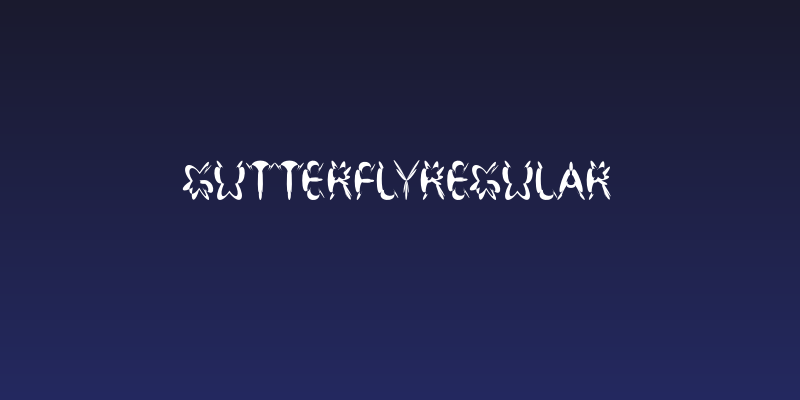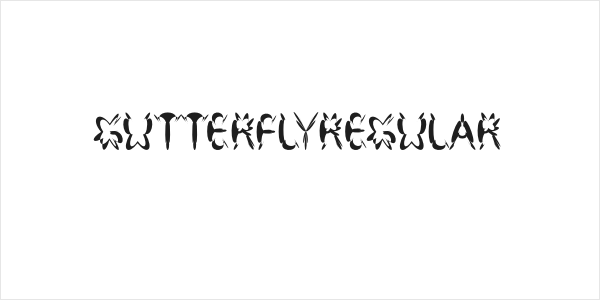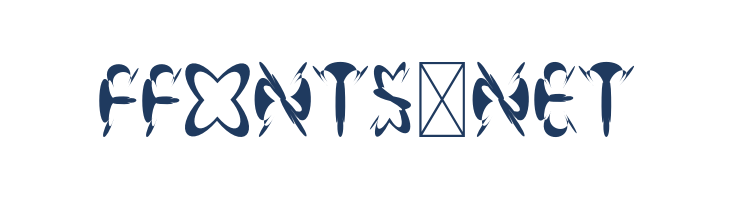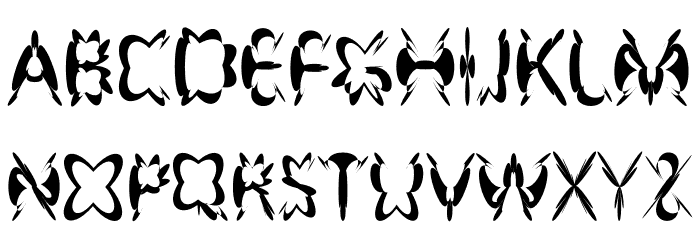
GutterflyRegular Font
✎ Decorative
| عائلة الخط | Gutterfly |
| الفئات | Decorative |
| حالة الاستخدام | Logos, Posters, Invitations |
| مشاريع مقترحة | Ideal for artistic projects, event invitations, posters, and branding that require a decorative and unique touch. |